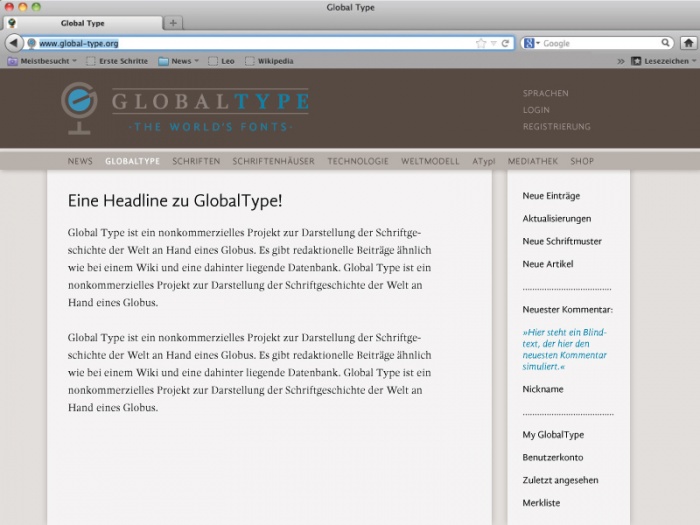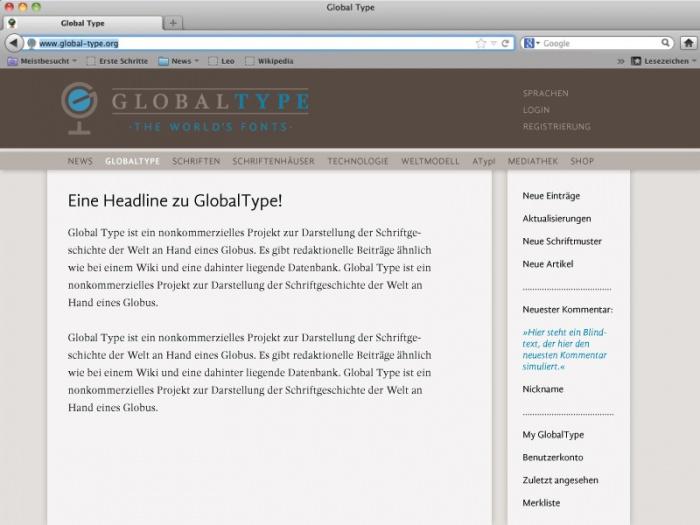
[GlobalType] Update
Seit wenigen Tagen ist das Update vollzogen. Wir sind auf einen neuen Server umgezogen, es gibt eine neue Datenbank und ein neues Typo3 (CMS). MySQL, HTML, CSS, PHP – alles up to date. Ich bedanke mich noch einmal ganz herzlich für die finanzielle Unterstützung hier aus dem Forum. Von dem Update seht Ihr zwar nichts, d.h. es gibt keinen sichtbaren Unterschied zum bisherigen Zustand, aber unter der Haube ist eine Menge passiert. Für Euch wird es richtig interessant, wenn das Relaunch soweit ist.
So – und hier nun das lang angekündigte neue Web Design. Aus diesem Entwurf, der aus Kathrins Feder stammt, wird jetzt ein HTML- bzw. Typo3-Template gebaut, aus dem dann später vollautomatisch die Unterseiten generiert werden.
Also auf Deutsch: Alle Seiten der Website sehen zukünftig so aus wie dieses Muster.
Zu den im Entwurf gezeigten Buttons und Texten sei gesagt, dass das jetzt einfach mal Blindtexte sind, das heißt, Lars muss noch festlegen, welche Buttonkategorien es im Einzelnen geben soll, welche Sonderfunktionen angeboten werden können, etc. Es ging in meinem Entwurf hauptsächlich darum, festzulegen, wie die Seite aufgeteilt wird, wie Farbe und Schrift verwendet werden und in welcher Form das neue Logo zum Einsatz kommt. Der Entwurf ist nicht in Stein gemeißelt – wenn Ihr sinnvolle Einwände/Ergänzungen habt, dann würde es mich sehr freuen, wenn Ihr sie mit uns teilt.  :-D
Etwas mehr Kontrast im Header würde die Sichtbarkeit der Menüpunkte "Registrierung : Login : Sprachen" erhöhen.
<tadelig erhobener Zeigefinger>Kathrin, Du hast Lars' tollen Witz ruiniert</tadelig erhobener Zeigefinger> Ich bekam zuerst einen Schreck der Kategorie "der wird doch nicht etwa...?"
Gefällt mir sehr gut. Wesentlich klarer, strukturierter, freundlicher, einladender als die bisherige Seite. Die Farbgebung/Der Kontrast im Kopf stört mich nicht im geringsten. Die Schriften sind sehr ansprechend. Das R der Gandhi gibt eine gute Figur ab. Der neue Globus sollte auch im Favicon eingesetzt werden.
[…] welche Buttonkategorien es im Einzelnen geben soll, welche Sonderfunktionen angeboten werden können […]
Trotzdem an dieser Stelle die Frage, ob es sinnvoll ist, wenn auf der deutschsprachigen Seite mit dem Wort »Sprachen« auf andere Sprachversionen aufmerksam gemacht wird. Wäre es nicht besser hier »Languages« zu schreiben?
<tadelig erhobener Zeigefinger>Kathrin, Du hast Lars' tollen Witz ruiniert</tadelig erhobener Zeigefinger> Ich bekam zuerst einen Schreck der Kategorie "der wird doch nicht etwa...?"
Ich hatte es gar nicht als Scherz in dem Sinne gemeint, dass jetzt die gesamte Website in Fraktur kommen soll, sondern wollte nur andeuten, dass ich jetzt quasi »Starckdeutsch« rede …